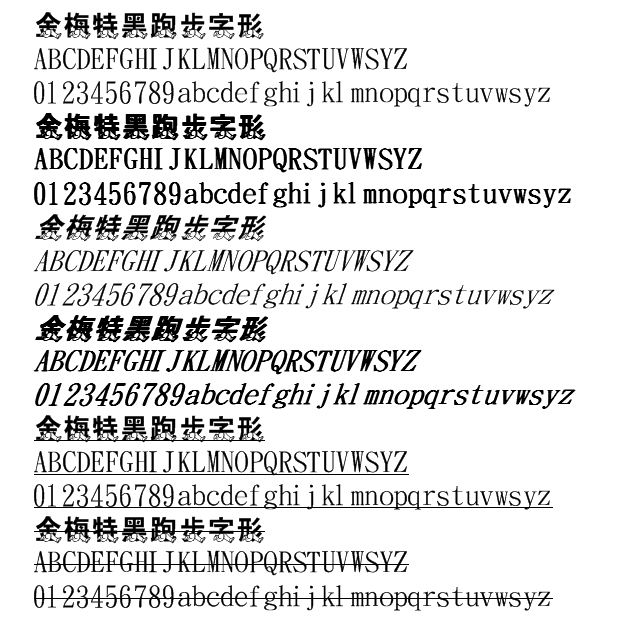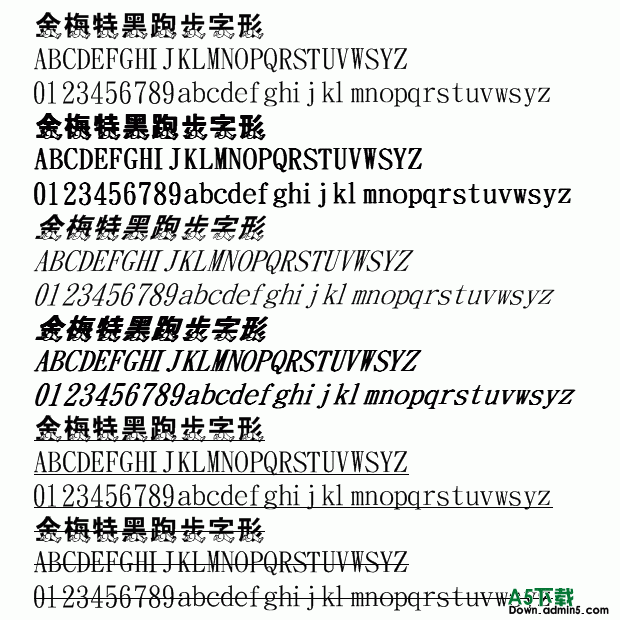
金梅特黑跑步字形字體是一款中文簡(jiǎn)體繁體字體,這款字體每個(gè)字下面都有一雙腿以跑步的樣子出行,看上去非常有意思,綠色資源網(wǎng)小編為大家提供免費(fèi)下載。
1.中國(guó)的字體設(shè)計(jì)是在印刷術(shù)的產(chǎn)生和發(fā)展中應(yīng)運(yùn)而生的。在古代,中國(guó)的字體設(shè)計(jì)曾有過(guò)輝煌的歷史時(shí)期,在宋朝時(shí)進(jìn)入黃金時(shí)代。
2.清朝末年,鉛字排版印刷術(shù)傳入中國(guó),字體設(shè)計(jì)進(jìn)入鉛字時(shí)代。這個(gè)時(shí)期的字體設(shè)計(jì)既要帶有傳統(tǒng)文化的審美慣性,又要符合鉛字印刷的工藝要求,字體設(shè)計(jì)走到了轉(zhuǎn)折的關(guān)口。
3.鉛字印刷是印刷走入機(jī)械化、工業(yè)化時(shí)代的標(biāo)志,但在這一時(shí)代里,印刷字體設(shè)計(jì)卻始終無(wú)法超越手工勞動(dòng)的制約,無(wú)法擺脫刻模、鑄字、撿字、排版等一系列印前繁雜工藝的束縛